De korte documentaire The Alphabeticians gaat over de mensen van de Cardozo Kindersley Workshop in Cambridge, waar de mooiste letters in steen worden gebeiteld, Na een reeks vertoningen in het VK is de film sinds 18 maart te zien op YouTube.
De eerste keer dat ik werk zag van David Kindersley (1915–1995) en Lida Lopes Cardozo (1954), was in het boek Glass Engraving van David Peace (B.T. Batsford, London, 1985).
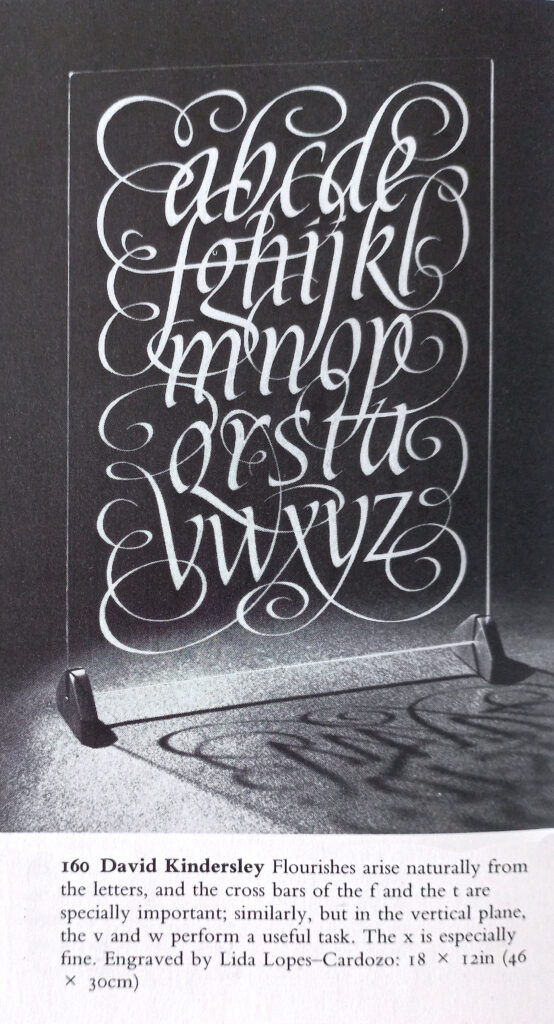
Glas graveren is min of meer een uitstapje voor de makers: hun werk is doorgaans in steen gebeiteld. Maar, zoals David Kindersley zei, ze zijn vooral alfabetici. Het is dus niet zo vreemd dat hij en Lida zich ook met typografie hebben beziggehouden.
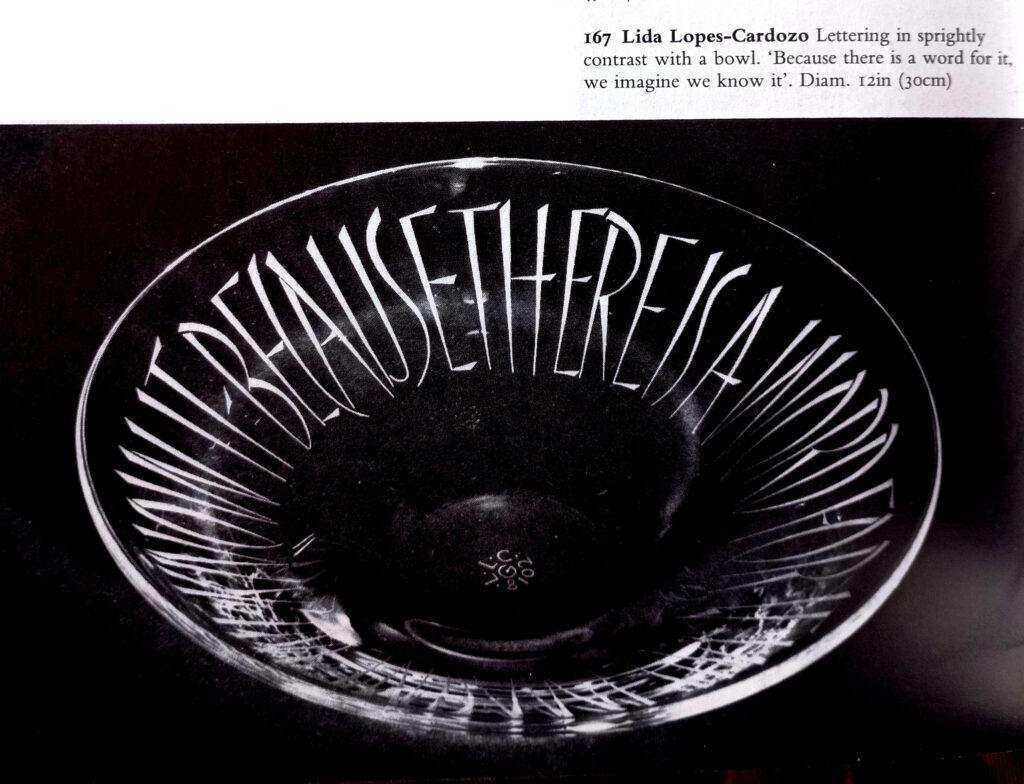
Lida Lopes Cardozo leerde het vak van David Kindersley, een leerling van Eric Gill (beeldend kunstenaar en ontwerper van van de Gill Sans, de Perpetua en andere lettertypen), die weer Edward Johnston als leraar had (calligraaf en ontwerper van de Johnston, lange tijd het lettertype voor de Londonse metro). Toch mooi hoe een ambacht wordt doorgegeven, en nu ook weer aan de volgende generatie.
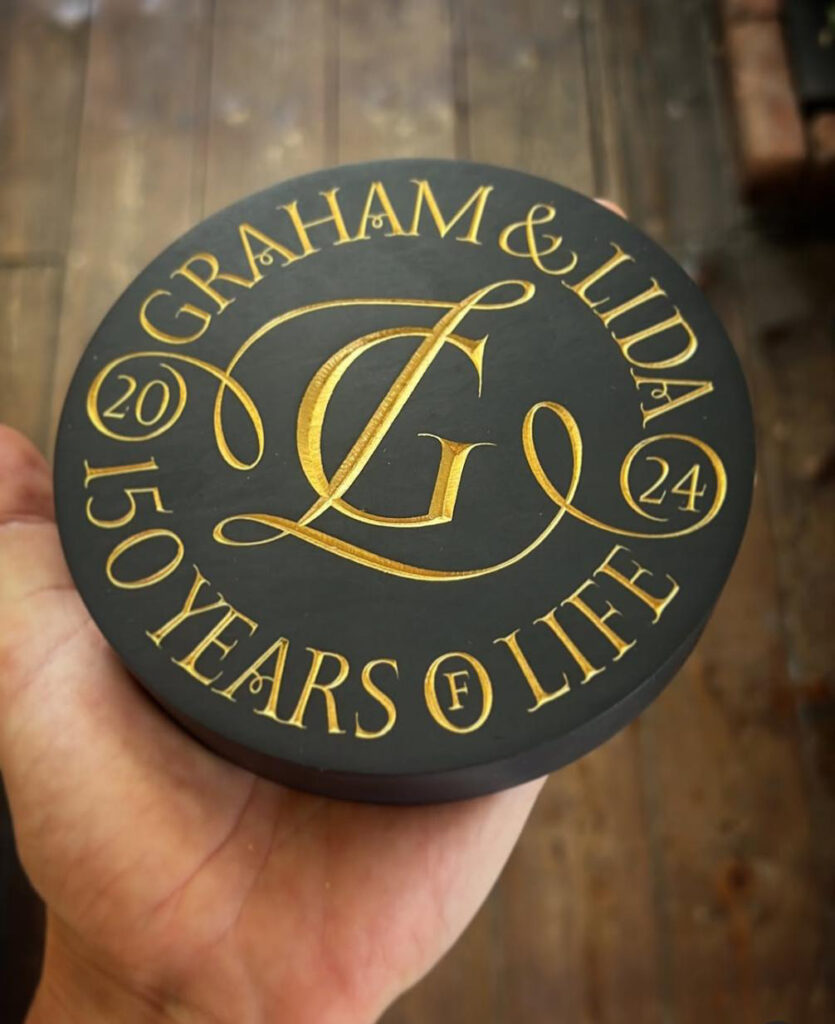
Via de Instagram-account van de werkplaats ontdekte ik dat er een documentaire in de maak was. Later werd die op diverse plaatsen in Engeland vertoond, maar naar Nederland leek The Alphabeticians niet te komen. Gelukkig werd de film de afgelopen week op YouTube gezet, en kon ik eindelijk zelf zien waar de letteraars zo blij mee waren.
De film geeft een mooie impressie van de Cardozo Kindersley Workshop en de mensen die daar werken. Door een belangrijke overgang voor de werkplaats gaat het ook over relaties, creativiteit en de erfenis voor de volgende generatie.